دانلود The Cute Fonts Bundle 20 فونت انگلیسی کارتونی و بامزه
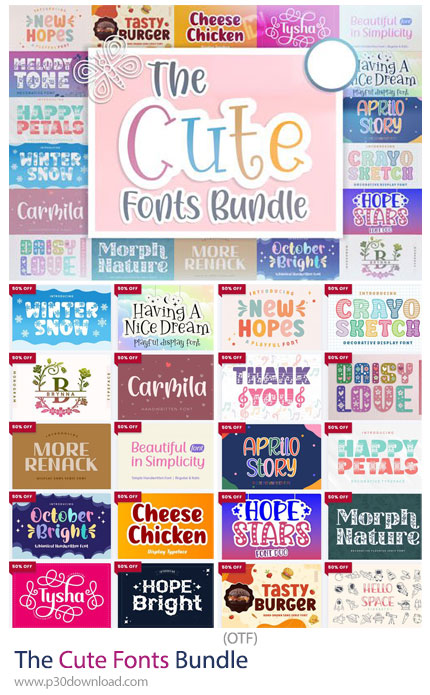
این مجموعه شامل 20 فونت انگلیسی کارتونی و بامزه است که با فرمت OTF بر روی سایت برای دانلود قرار گرفته است. The Cute Fonts Bundle یکی از محبوبترین باندلهای فونت در تمام سایتهای معتبر است که مخصوص طراحان، اینستاگرامرها، بلاگرها، برندهای کودکانه، عروسی، لوازم تحریر، کافه، بوتیک و هر چیزی که نیاز به حس ناز، بانمک، گرم و دوستداشتنی دارد، طراحی شده است.